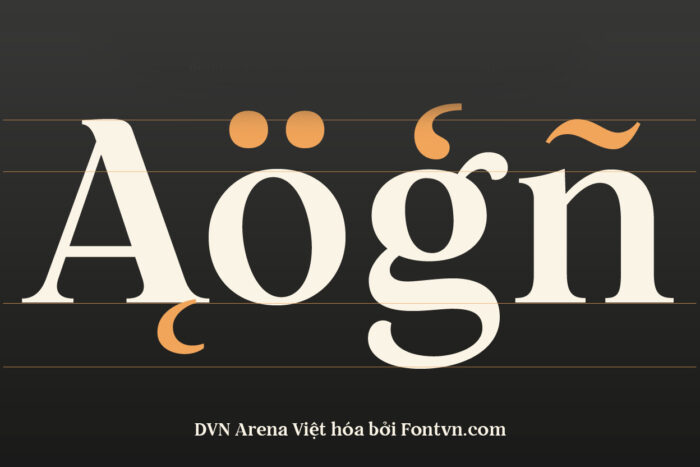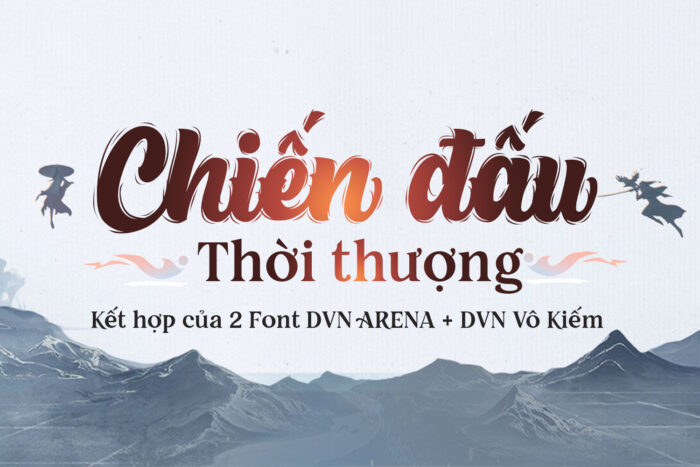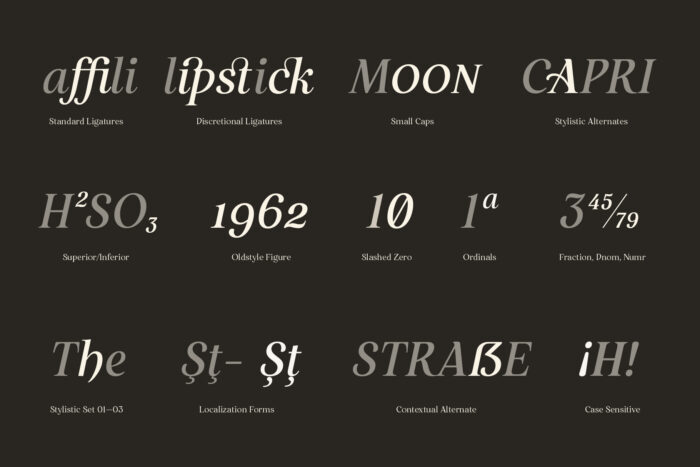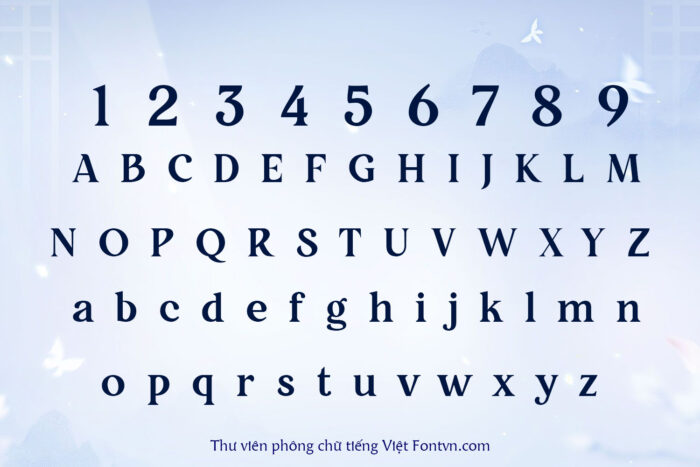
DVN ARENA Việt hóa – Font chữ cổ điển phù hợp cho sự tinh tế và gaming
Font chữ Arena mang đến vẻ đẹp tinh tế, pha trộn giữa phong cách cổ điển và hiện đại. Với các nét đậm, chắc chắn, font chữ này thể hiện sự mạnh mẽ nhưng vẫn giữ được sự mềm mại và thanh thoát nhờ các đường cong mượt mà. Arena phù hợp cho các dự án thiết kế liên quan đến thương hiệu cao cấp, biên tập sách, và các ấn phẩm quảng cáo, nơi cần sự sang trọng và sự chuyên nghiệp. Phần khoảng cách giữa các chữ cái được tối ưu giúp tăng khả năng đọc, dù là ở cỡ chữ lớn hay nhỏ. Arena dễ dàng ứng dụng trong nhiều ngữ cảnh khác nhau, từ thiết kế đồ họa đến truyền thông số, mang đến sự thu hút và dễ nhận diện cho người xem.
Font có hỗ trợ Ligature và Glyphs giúp bạn tạo ra hiệu ứng chữ tuyệt đẹp, xem hướng dẫn dùng Ligature và Glyphs tại đây